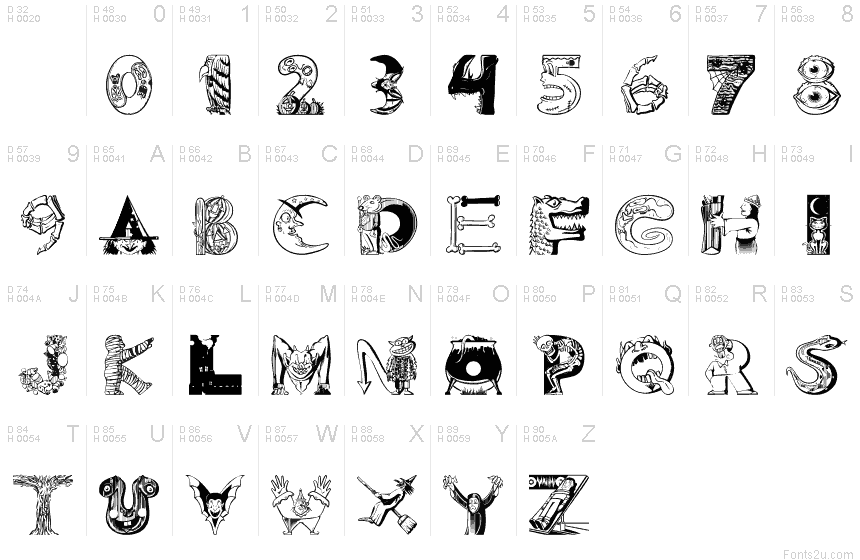
101! 'Ween by Nght to darmowy krój pisma typu display na Halloween, zbudowany z groteskowych, odręcznie rysowanych figur zamiast konwencjonalnych form geometrycznych. Każdy symbol przypomina małą kreskówkę grozy.
Nawiedzona atrakcja lub sezonowa marka słodyczy mogłaby go użyć do plakatów, opakowań, grafik na wydarzenia i gadżetów, gdzie napis staje się częścią dzieła sztuki. Pióra, wpatrzone oczy, rozwarte usta, podniesione ręce i przebrane ciała zmieniają znaki w miniaturowe maskotki o radosnym, makabrycznym motywie.